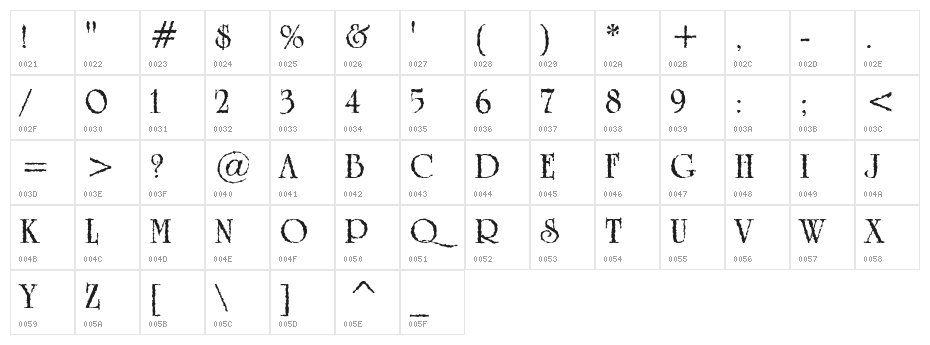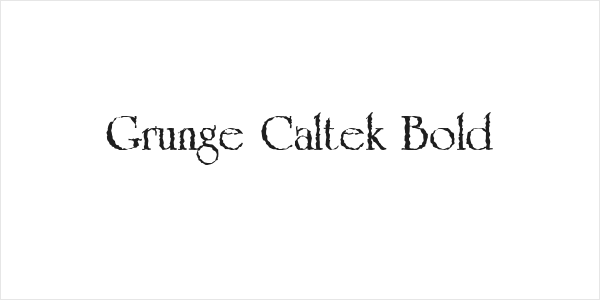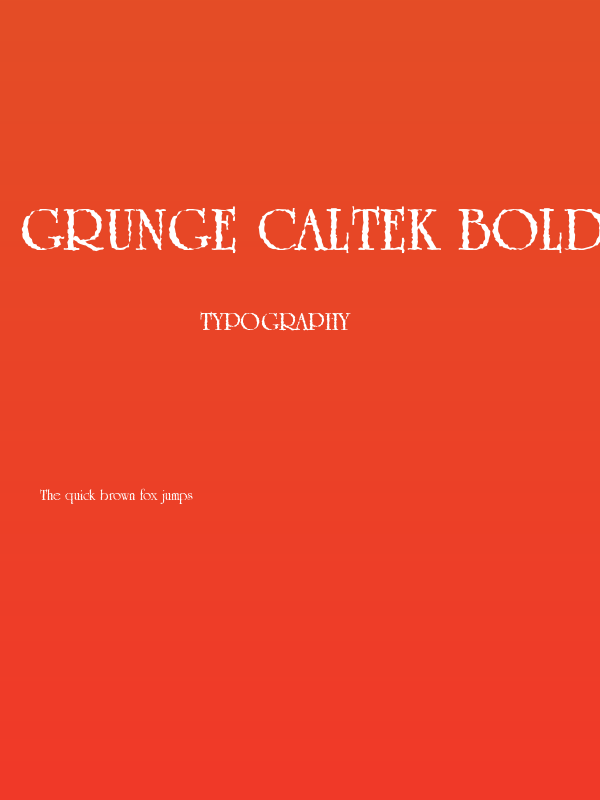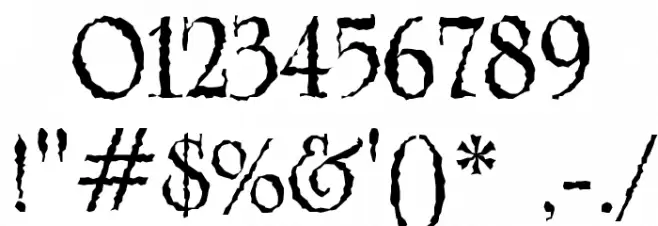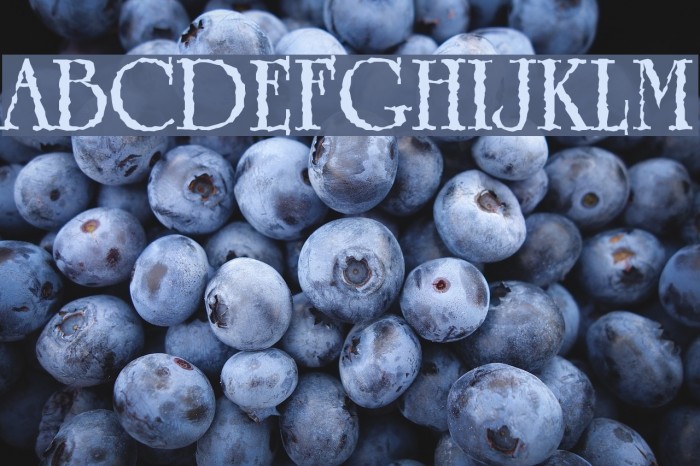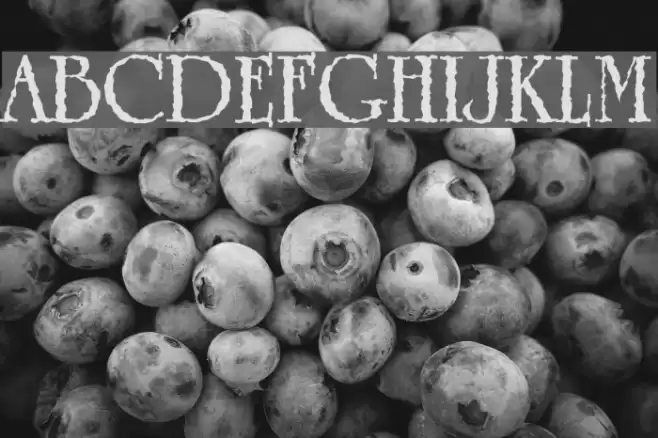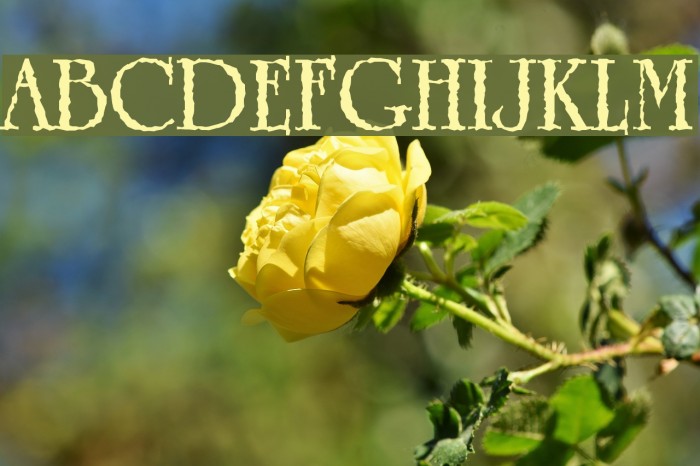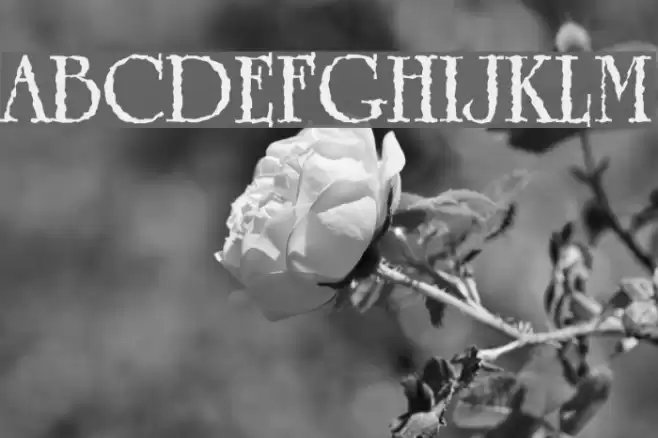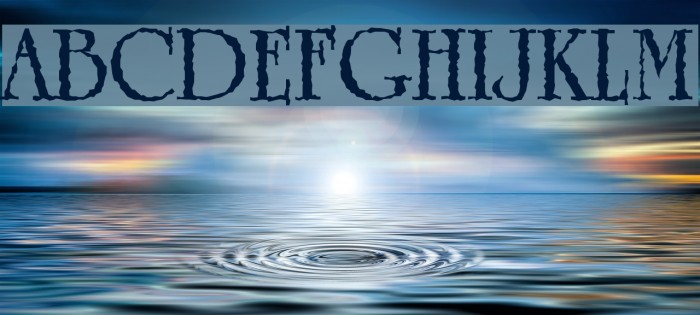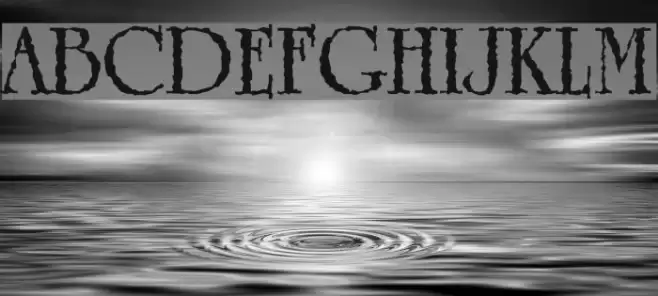
Grunge Caltek Bold Font
| 整体风格 | Grunge, Decorative |
| 推荐项目 | Ideal for album covers, posters, and branding projects that require a bold, edgy aesthetic. |